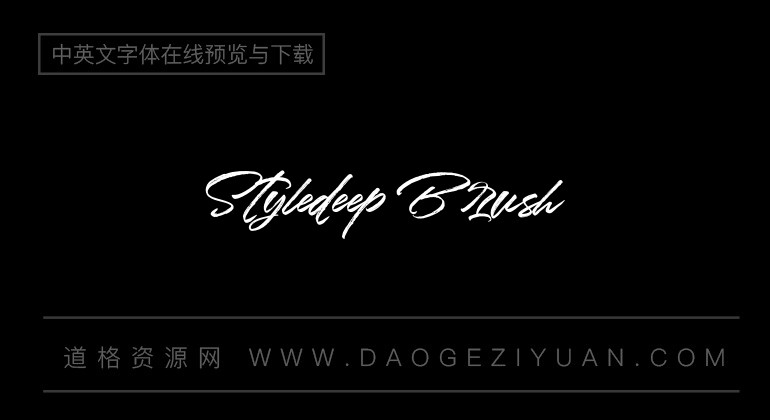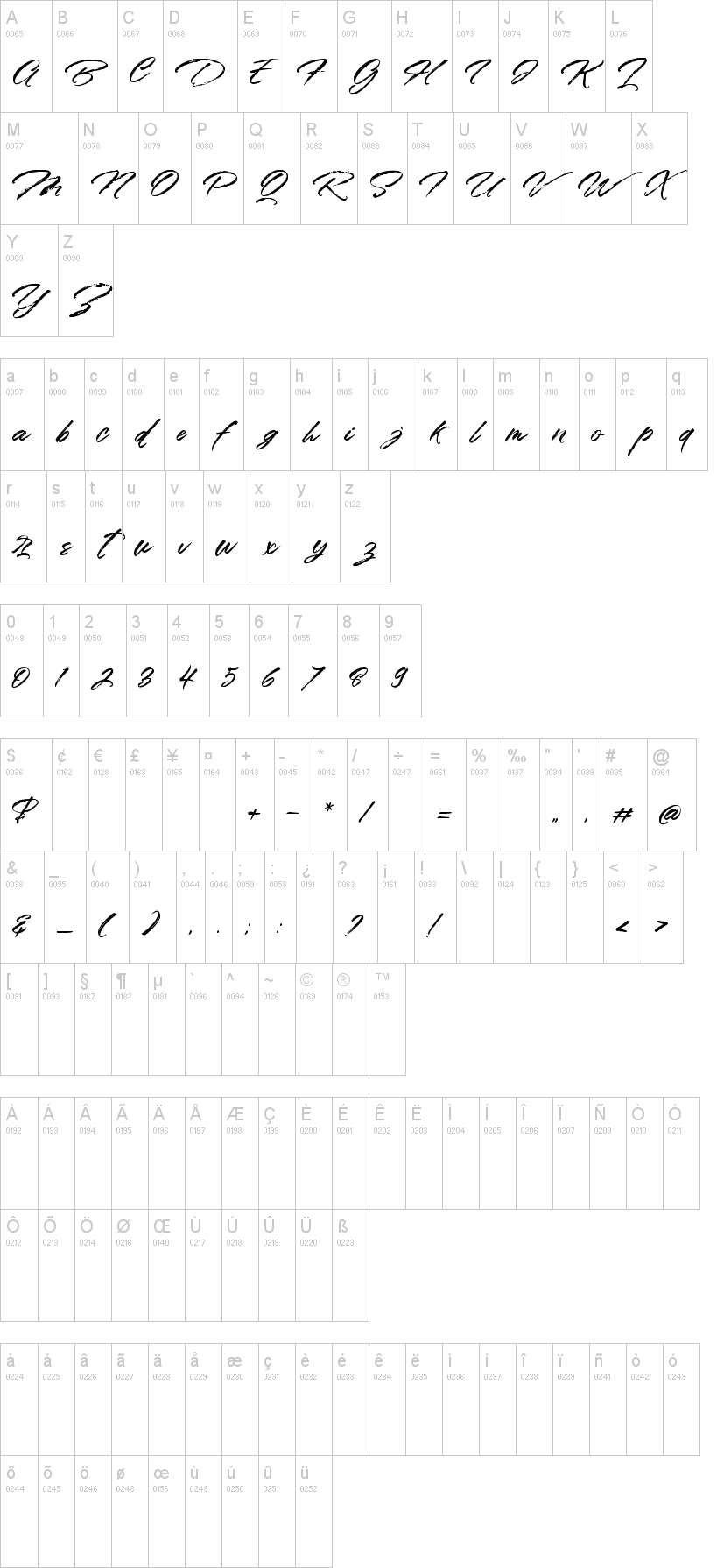
Styledeep Brush 字体是一款非常漂亮、极具艺术感的手写创意字体。它的特点是线条流畅、自然,仿佛是由一支毛笔写出来的一样。同时,Styledeep Brush 字体的字形设计也非常独特,每个字母都有自己的特点和风格,具有很高的辨识度。 Styledeep Brush 字体适用于各种创意和艺术设计场景,比如海报、宣传册、书籍封面、标志、印刷品等等。它的特殊风格能够让你的设计更加出彩,给人留下深刻的印象。此外,它也适合用于头像、个性签名等场景,让你的个性展现得淋漓尽致。内容介绍
Styledeep Brush是一款非常不错的手写艺术字体,具有很好的视觉感,适合于文化类的宣传设计、商业类品牌的广告和产品包装设计以及个性化文字排版等较多场景。